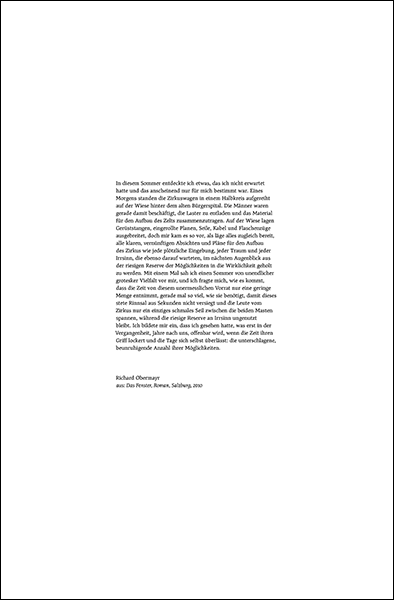
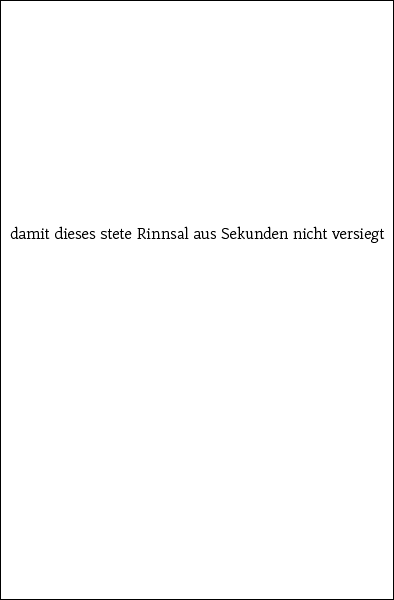
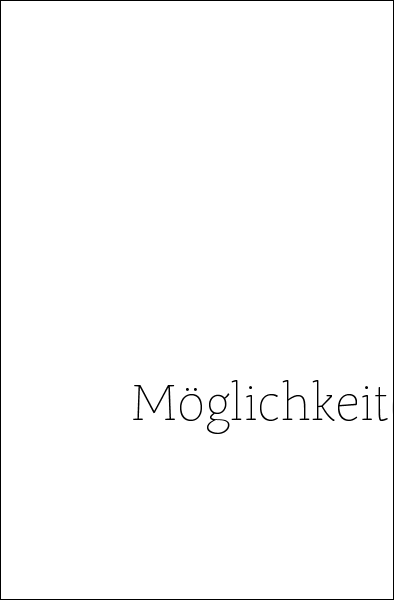
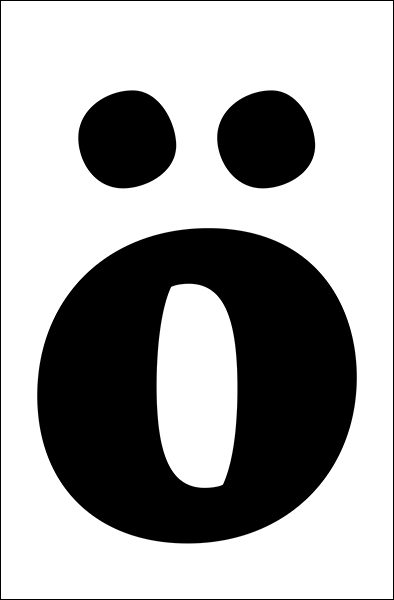
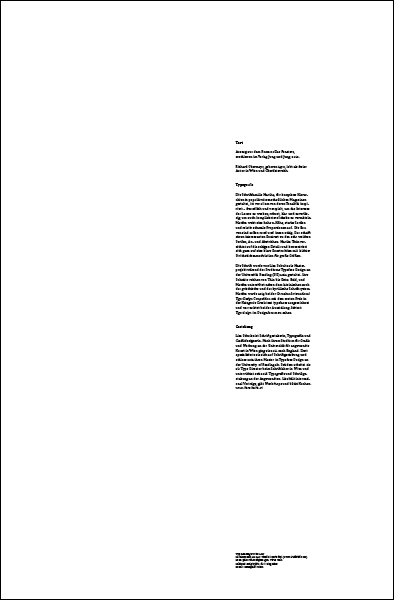
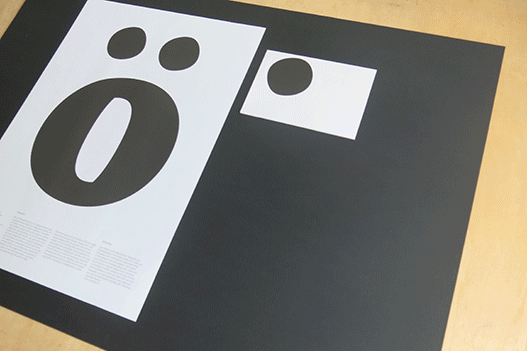
Text
Auszug aus dem Roman Das Fenster, erschienen im Verlag Jung und Jung, 2010. Richard Obermayr, geboren 1970, lebt als freier Autor in Wien und Oberösterreich.
Typografie
Die Schriftfamilie Martha, für komplexe Hierarchien in populärwissenschaftlichen Magazinen gestaltet, ist vor allem von deren Tonalität inspiriert – freundlich und verspielt, um das Interesse des Lesers zu wecken, robust, klar und zuverlässig, um auch kompliziertere Inhalte zu vermitteln. Martha weist eine hohe x-Höhe, starke Serifen und relativ schmale Proportionen auf. Die Kurven sind außen rund und innen eckig. Das schafft einen interessanten Kontrast zu den sehr weichen Serifen, An- und Abstrichen. Martha Thin verzichtet auf die eckigen Details und konzentriert sich ganz auf eine klare Konstruktion mit leichter Strichstärkenmodulation für große Größen.
Die Schrift wurde von Lisa Schultz als Masterprojekt wärend des Studiums Typeface Design an der Universität of Reading (UK) 2012 gestaltet. Ihre Schnitte reichen von Thin bis Extra Bold, und Martha unterstützt neben dem lateinischen auch das griechische und das kyrillische Schriftsystem. Martha wurde 2013 bei der Granshan International Type Design Competition mit dem ersten Preis in der Kategorie Greek text typefaces ausgezeichnet und war zuletzt bei der Ausstellung subtext: typedesign im Designforum zu sehen.
Gestaltung
Lisa Schultz ist Schriftgestalterin, Typografin und Grafikdesignerin. Nach ihrem Studium für Grafik und Werbung an der Universität für angewandte Kunst in Wien ging sie 2011 nach England. Dort spezialisierte sie sich auf Schriftgestaltung und schloss 2012 ihren Master in Typeface Design an der University of Reading ab. Seitdem arbeitet sie als Type Director beim Schriftlabor in Wien und unterrichtet seit 2016 Typografie und Schriftgestaltung an der Angewandten. Lisa hält international Vorträge, gibt Workshops und bäckt Kuchen.